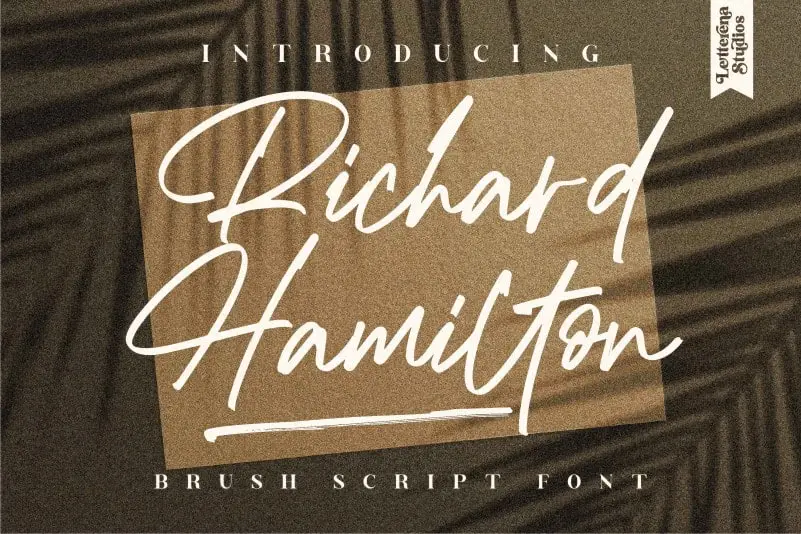
Richard Hamilton Handwritten Font – Download Grátis
Richard Hamilton Handwritten Font é uma fonte escrita a mão moderna projetada pelo designer letterenastudios. Esta elegante seleção de letras foi criada para satisfazer uma variedade de necessidades gráficas, abrangendo desde os logos e projetos de marca até as etiquetas e selos. Suas linhas finas e seus detalhes suaves tornam-a ideal para aplicações como design de móveis, embalagens de produtos, calçados, adesivos, e muito mais. Seja para imprimir em um livro ou criar uma tarja de nome, esta fonte oferece uma expressão única que encaixa-se perfeitamente com os projetos exigentes e requintados na sua lista de tarefas. Com o Richard Hamilton Handwritten Font, você pode adicionar ao seu design a autêntica mão de um artista gráfico no seu próximo projeto.